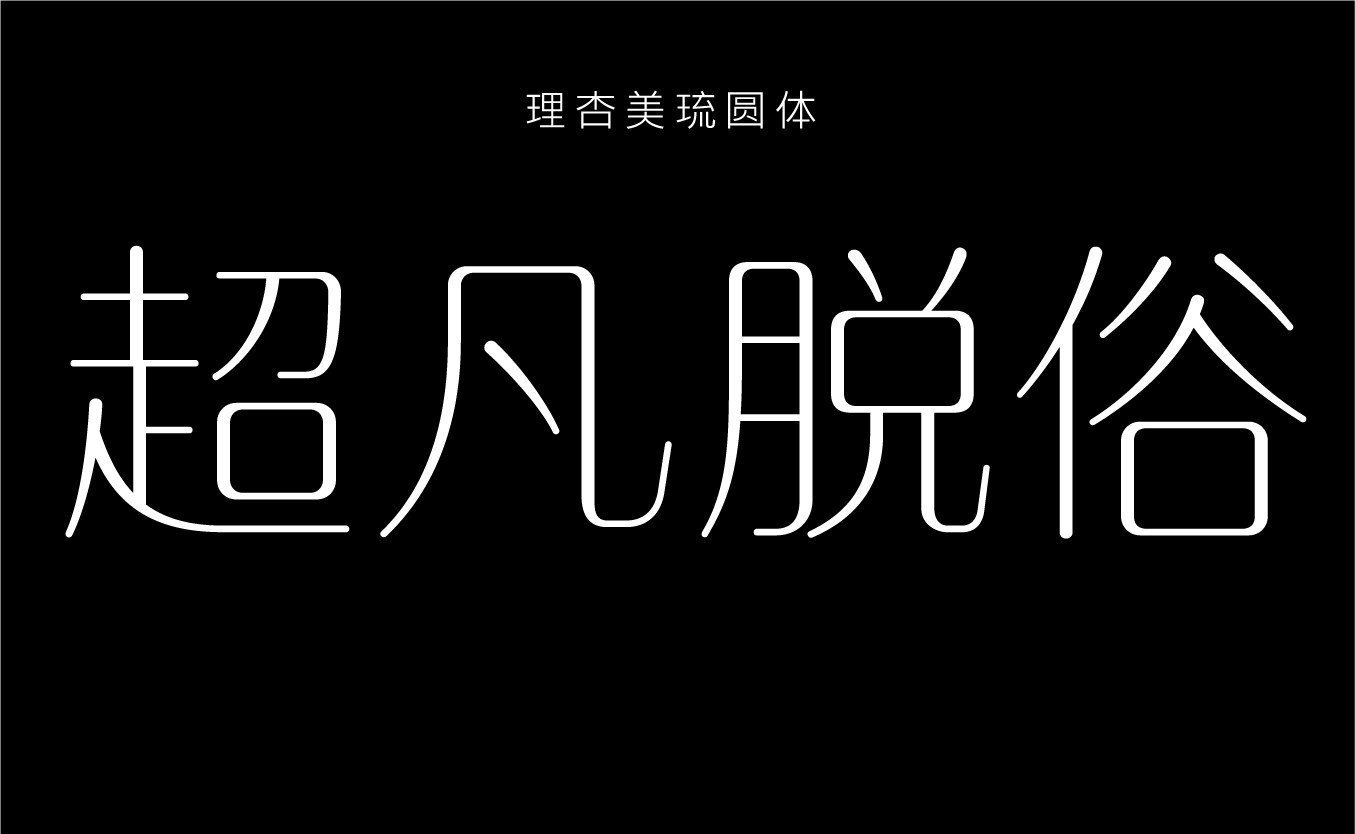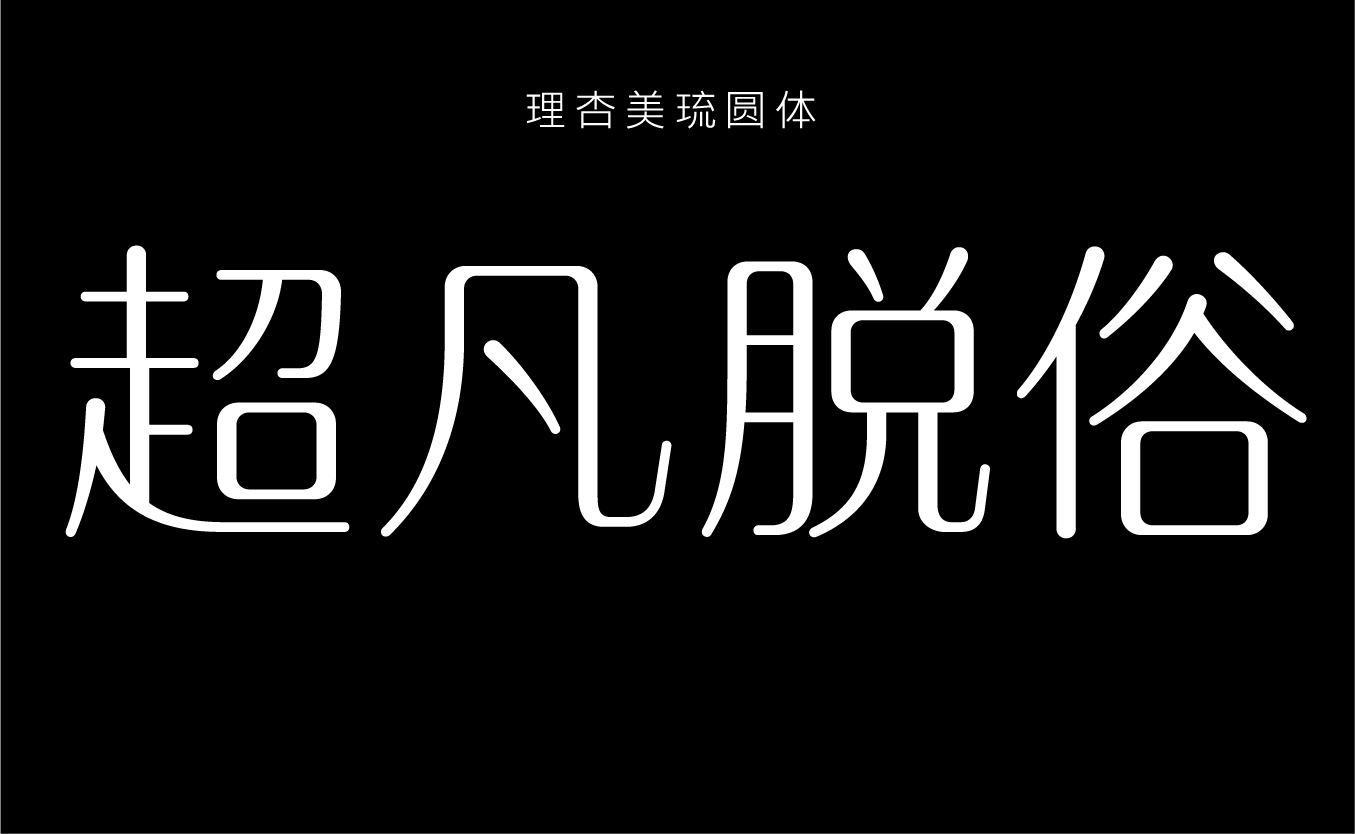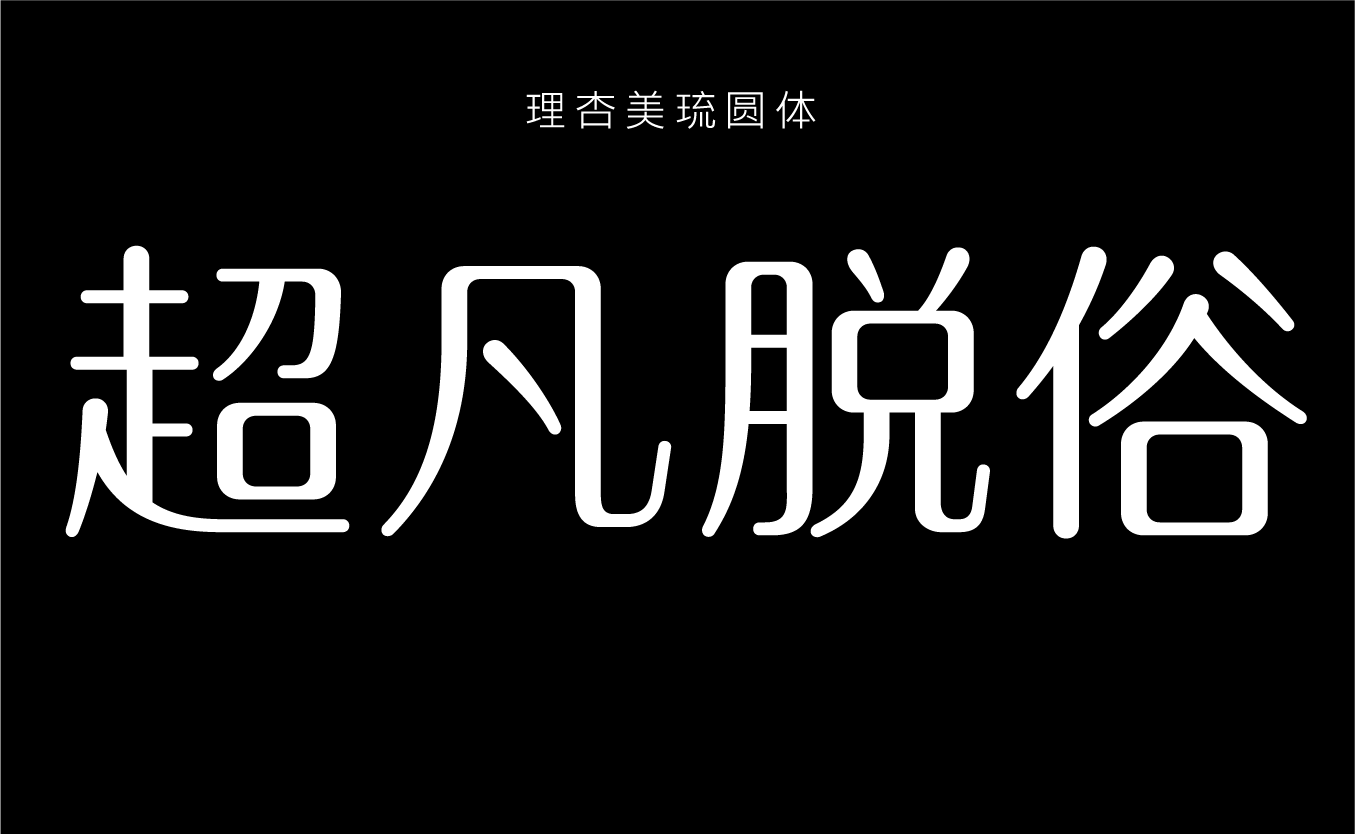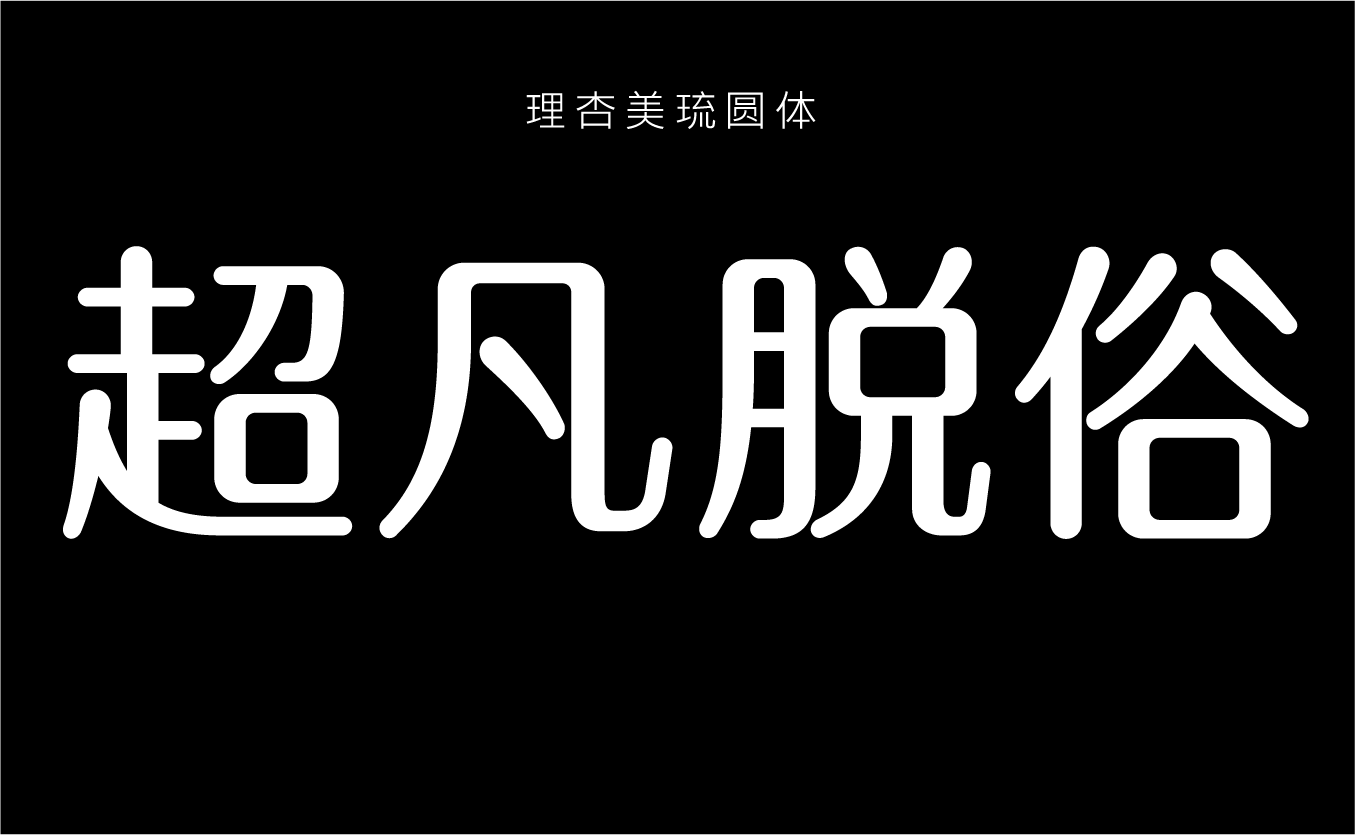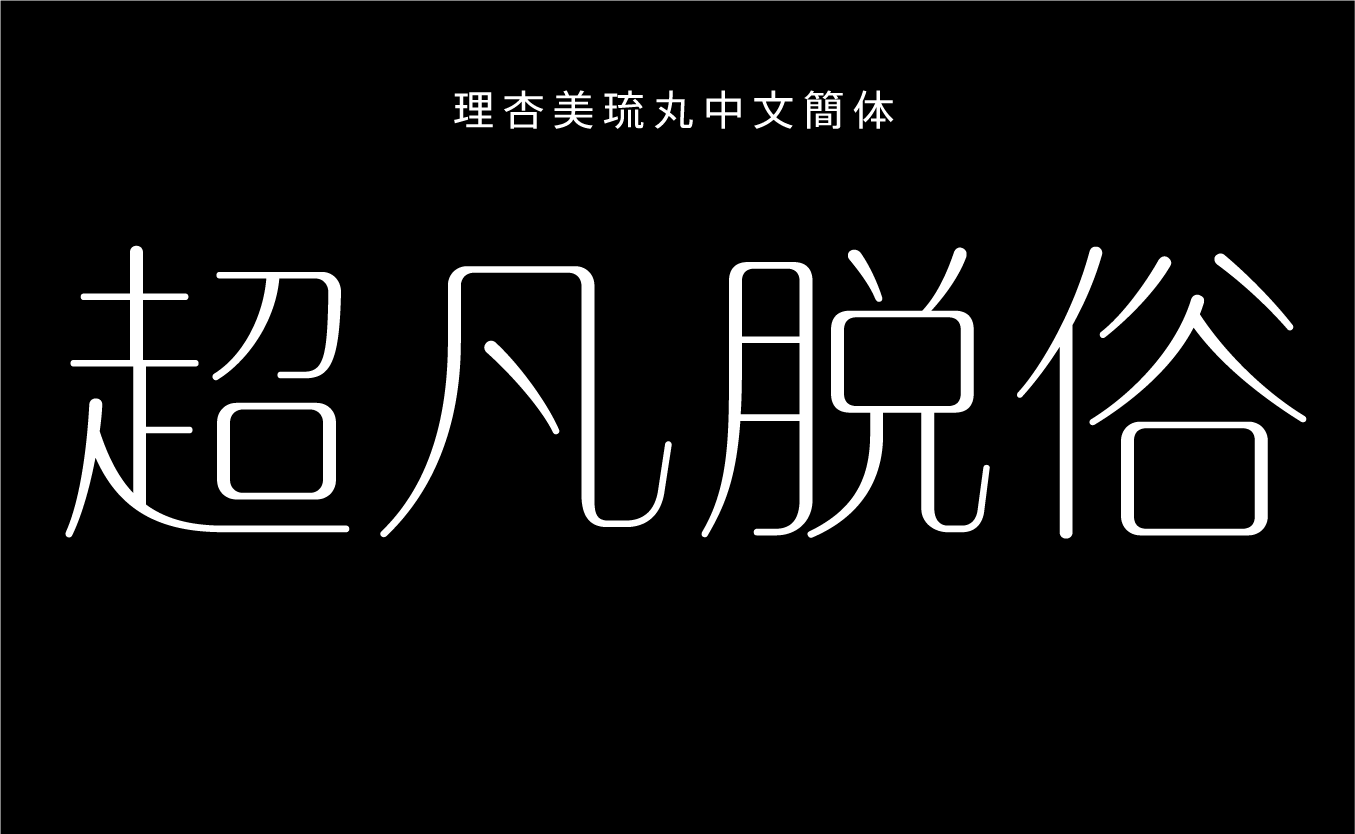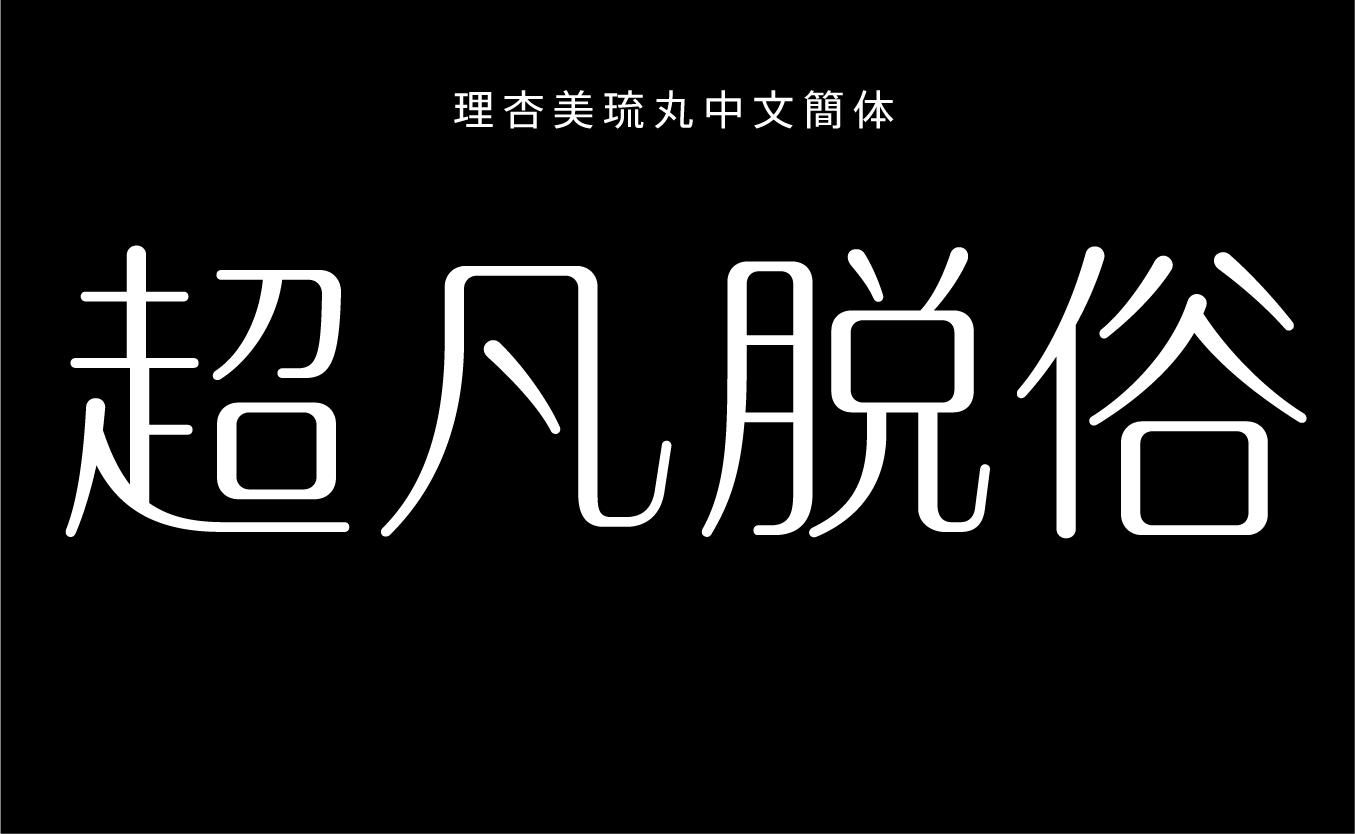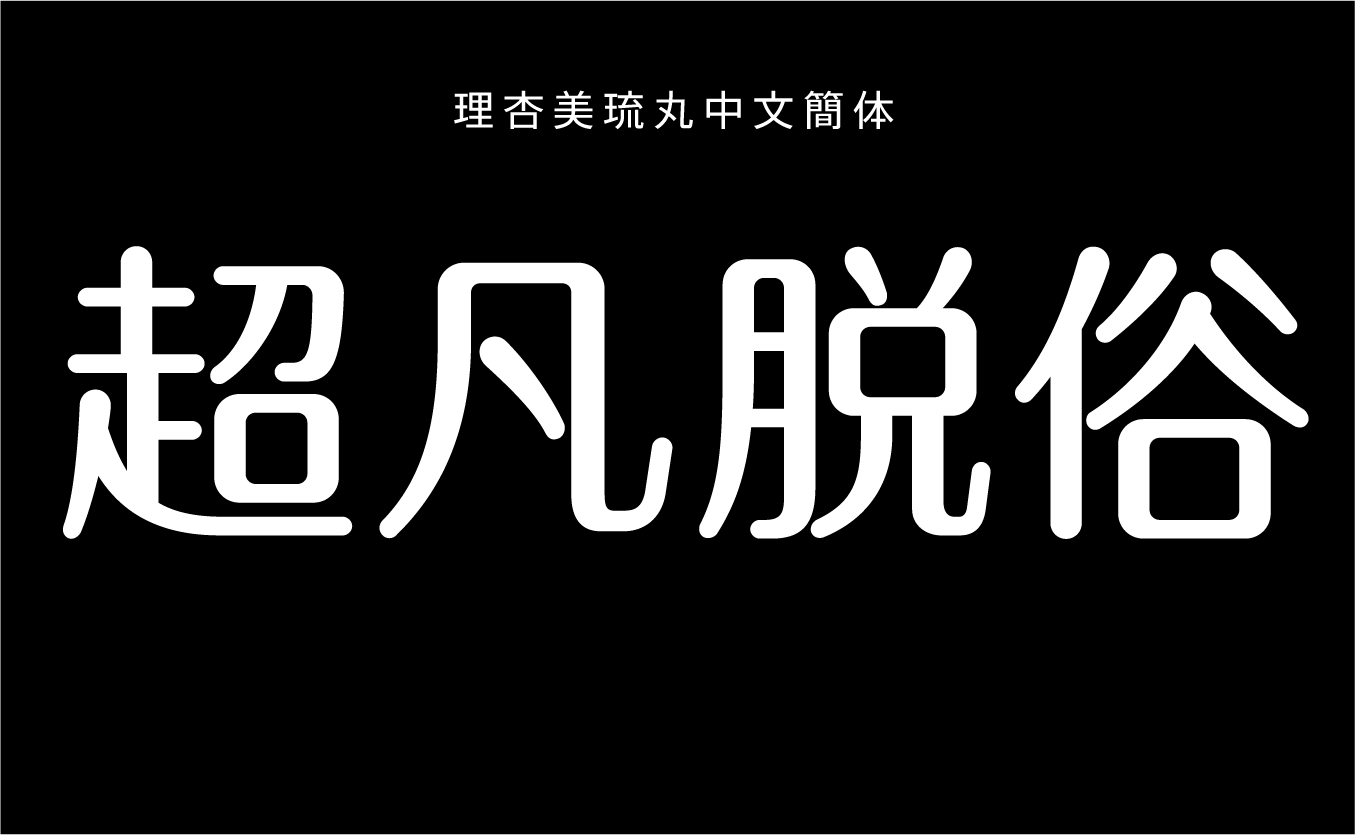
理杏美琉丸体ファミリーは、美琉体をベースに、縦線、横線、点、トメ、ハネ、ハライなど、各パーツの先端を丸く処理したデザイン書体です。独特な丸明朝体系のフォルムで、柔らかくスマートな印象とともに、優しい雰囲気を醸しだします。美琉体同様4ウエイトを揃え、本文組だけでなく、見出しやロゴデザインなどにも適しています。
理杏美琉丸中文簡体 L
理杏美琉丸中文簡体 R
理杏美琉丸中文簡体 M
理杏美琉丸中文簡体 DB